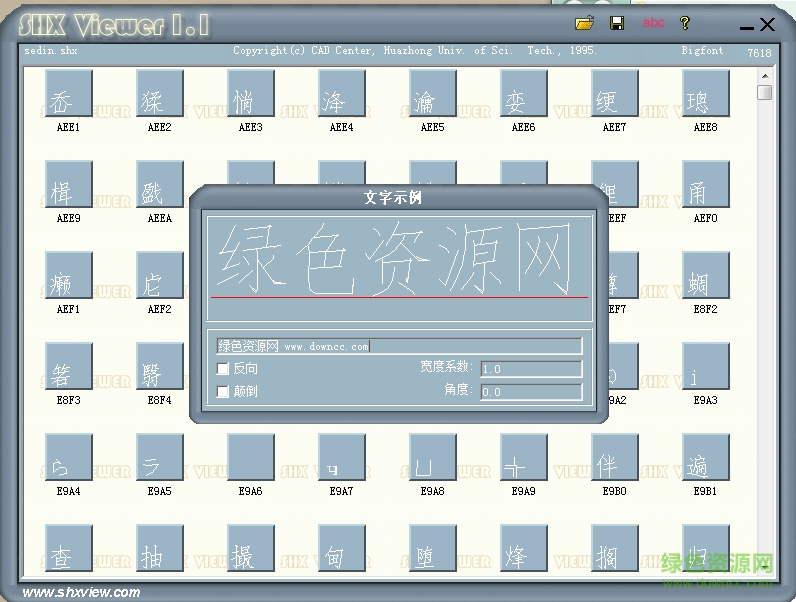
sedin字體是cad中方便查看圖紙的必備字體,很多朋友找不到這款字體,造成圖紙無(wú)法打開或識(shí)別,綠色資源網(wǎng)為大家?guī)?lái)這款字體,幫助大家解決設(shè)計(jì)上的困難!
sedin.shx擁有7618個(gè)漢字組成,屬于bigfonts系列,文字有著流暢的線條和較小的形態(tài),讓圖紙中的漢字看起來(lái)更加簡(jiǎn)潔和干練。